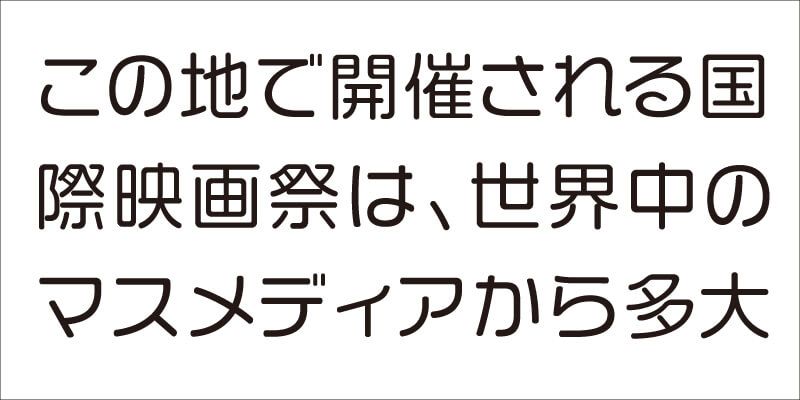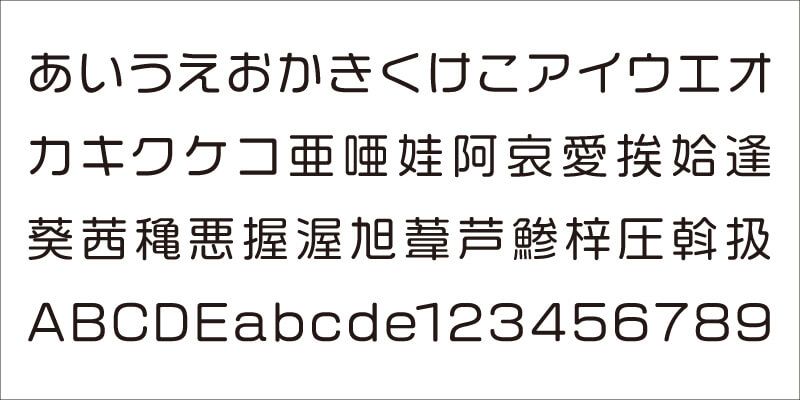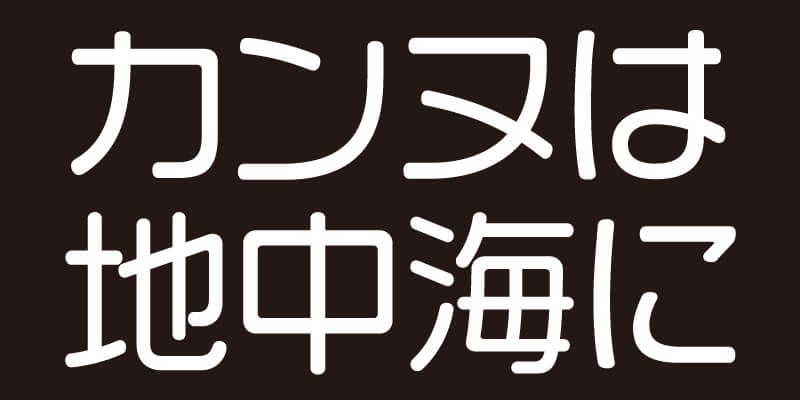
VDL-LogoG의 디자인을 바탕으로 만들어진 VDL-LogoMaru는 부드러운 곡선, 넓은 카운터 공간, 둥근 획의 시작과 끝이 특징인 친근한 모양의 둥근 고딕(산세리체) 글꼴입니다.
Visual Design Laboratory(VDL)의 기업정신은 레터폼의 자연미와 가독성의 엄격한 기준을 균형 있게 유지하는 것입니다. VDL에서는 포괄적인 “VDL Designers Fonts”(VDL ザ イ ナ ー ズ フ ォ ン ト) 컬렉션을 제공함으로써 고객에게는 다양한 인상을 심어주고 독자적인 서체를 찾는 디자이너와는 공감할 수 있습니다.